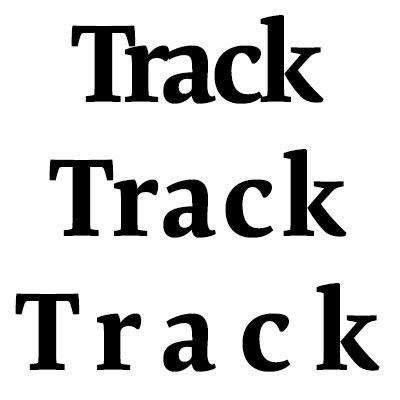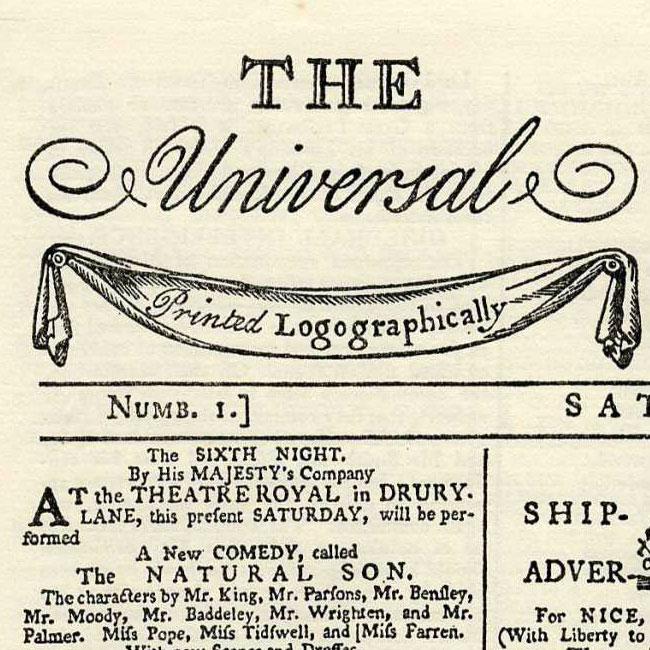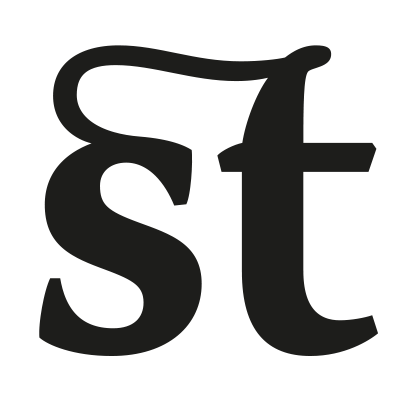
Das lange s (ſ) ist eine grafische Variante des Buchstabens s. Das Zeichen entstand durch eine Streckung des Versal-S und kam in der karolingischen Minuskel als alleinige Repräsentation des s-Graphems zum Einsatz. Im 15. und 16. Jahrhundert setzt sich dann in Druck- und Handschriften im lateinischem Schriftsystem eine gemeinsame Anwendung von langem und rundem s durch – zunächst gänzlich unabhängig von Schriftstil und Sprache. Die Wahl zwischen ſ und s erfolgte stellungsbasiert. Worts
Langstrich ist eine in der DIN 5008 benutzte Bezeichnung für den Halbgeviertstrich.
Die Laufweite (englisch: Tracking) bezeichnet den generellen Buchstabenabstand einer Schrift. Im Digitalsatz kann die Laufweite als einzelner Parameter heute beliebig und – im Gegensatz zum Bleisatz – auch bis in den negativen Bereich variiert werden. Ist die Laufweite Null, schließen alle Buchstabenkegel direkt aneinander an. Ist die Laufweite größer Null, besteht ein Abstand zwischen den Buchstabenkegeln. Ist die Laufweite negativ, werden die Buchstabenkegel übereinander geschoben.
Wenn ein Schriftsetzer im Bleisatz ein Wort oder eine Zeile des Manuskriptes ausgelassen hat, wird dies im Fachjargon Leiche genannt.
Die Lesbarkeit beschreibt die Verständlichkeit von Informationen. Im Gegensatz zur eher objektiv einschätzbaren Leserlichkeit ist die Lesbarkeit jedoch immer von einem Subjekt abhängig. Ein fremdsprachiger Text kann leserlich präsentiert sein, aber er ist für den einzelnen deshalb nicht zwangsläufig auch lesbar. Zu den Einflussgrößen der Lesbarkeit zählen unter anderem: Darstellung der Textinformation (siehe Leserlichkeit) Satzbau und Sprachstil Inhalt und dessen Komplexität Subjekta
Die Lesefreundlichkeit beschreibt, inwieweit eine Schrift und das gegebenenfalls mit ihr gesetzte Schriftbild so gestaltet sind, dass man den Text auch auf Dauer bequem und ermüdungsfrei lesen kann. Die Art der Informationsdarbietung sollte dafür zunächst leserlich (entzifferbar) und lesbar (verständlich) sein. Die Lesefreundlichkeit beschreibt eine darüber hinaus gehende Eigenschaft. So können etwa die Buchstaben einer Monospaced-Schrift problemlos lesbar sein. Aber wegen ihrer gleichförmigen
Die Leserlichkeit beschreibt, wie gut oder schlecht Informationen objektiv aufgenommen beziehungsweise entziffert werden können. Zu den Einflussfaktoren der Leserlichkeit zählen unter anderem: Textabhängige Einflüsse (Schriftart, Schriftgröße, Textmenge, Layout, Kontrast etc.) Zeichenträgerabhängige Einflüsse (Material, Glanzeigenschaften etc.) Situationsabhängige Einflüsse (Abstand, Sichtwinkel, Lichtverhältnisse etc.) Anforderungen für optimale Leserlichkeit unter verkehrsüblich
Der englische Begriff Lettering hat je nach Kontext unterschiedliche Bedeutungen: 1. Allgemeinsprachlich In der Allgemeinsprache beschreibt lettering als Partizip Präsens von letter ganz allgemein den Einsatz von Buchstaben, etwa im Sinne des deutschen Begriffes »Beschriftung«. (siehe Wiktionary) 2. In der Typografie Als typografischer Fachbegriff bezeichnet Lettering eine spezifische Art, Textinformationen zu entwerfen. Beim Lettering werden Buchstaben oder Wörter einzeln fü
LF ist die Abkürzung für Lining Figures – im deutschen Sprachraum in der Regel als Versalziffern bezeichnet.
Das Satztechnische Lexikon (1925) definiert licht als »alle zart, fein gezeichneten Schriften«, die sich damit insbesondere von den »kräftig, fett, schwarz gezeichneten Schriften unterscheiden«. Außerdem wird betont: »Konturschriften sind hier nicht einzureihen.« Ungeachtet dieser Definition benutzten die Schrifthersteller im deutschsprachigen Raum die Bezeichnung »licht« insbesondere für solche Konturschriften, die heute, im Zuge der Globalisierung meist mit dem Zusatz »outline« bezeichnet
Bezeichnung für Groteskschriften in der Schriftklassifikation DIN 16518
Eine Logotype (Plural Logotypen) bezeichnet in der Drucktechnik (Handsatz) einen Schriftkegel mit mehreren Buchstaben oder ganzen Wörtern. Das Wort bildet sich aus dem altgriechischen λόγος (lógos: sinnvolles Wort) und der Type (→ Letter, Schriftkegel). Logotypensatz als Technik Mit Logotypensatz (»Logotypie«) zur Beschleunigung des Handsatzes wurde mindestens seit dem 18. Jahrhundert experimentiert. Statt Einzellettern zu benutzen, werden mehrere Zeichen auf einen Kegel gegoss
Mit Logotypensatz (»Logotypie«) zur Beschleunigung des Handsatzes wurde mindestens seit dem 18. Jahrhundert experimentiert. Statt Einzellettern zu benutzen, werden mehrere Zeichen auf einen Kegel gegossen und die nötigen Handgriffe des Setzers somit reduziert. Zeitweise wurde die Logotypie beim Druck der Londoner Times angewandt. Bei einem Logotypensatzwettbewerb in Wien im Jahre 1883 wurde eine Höchstleistung von 3500 Zeichen in der Stunde erreicht. Dennoch konnte sich die Technik nicht auf bre